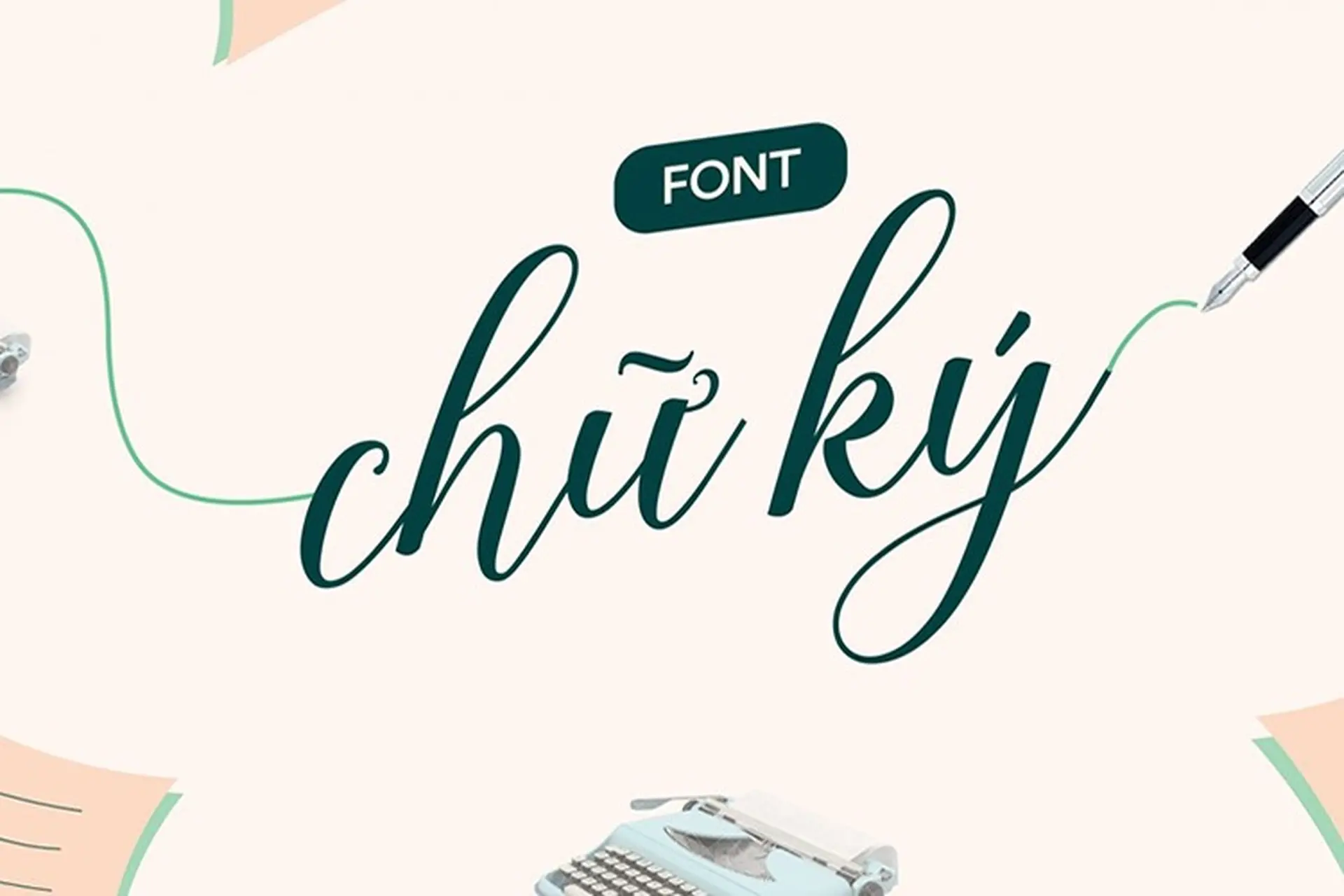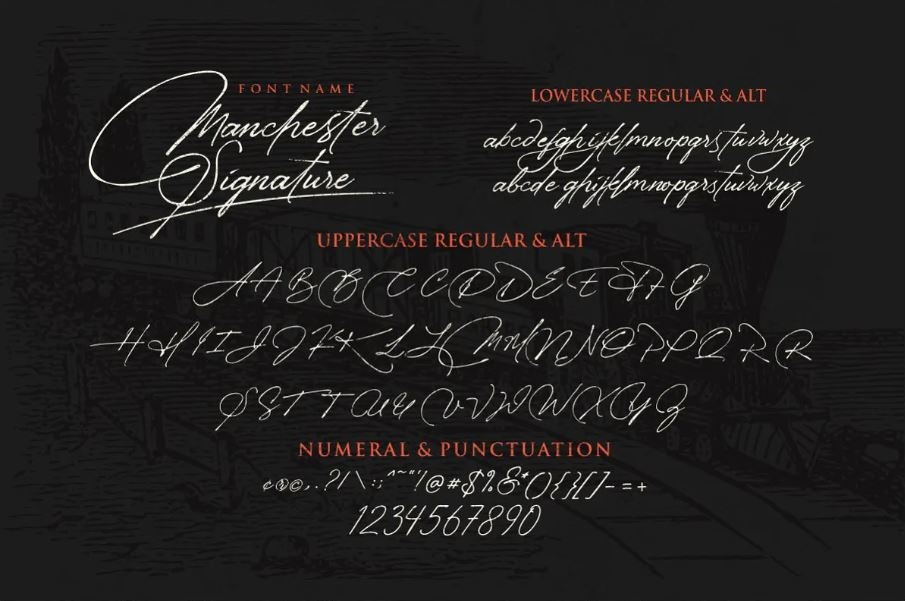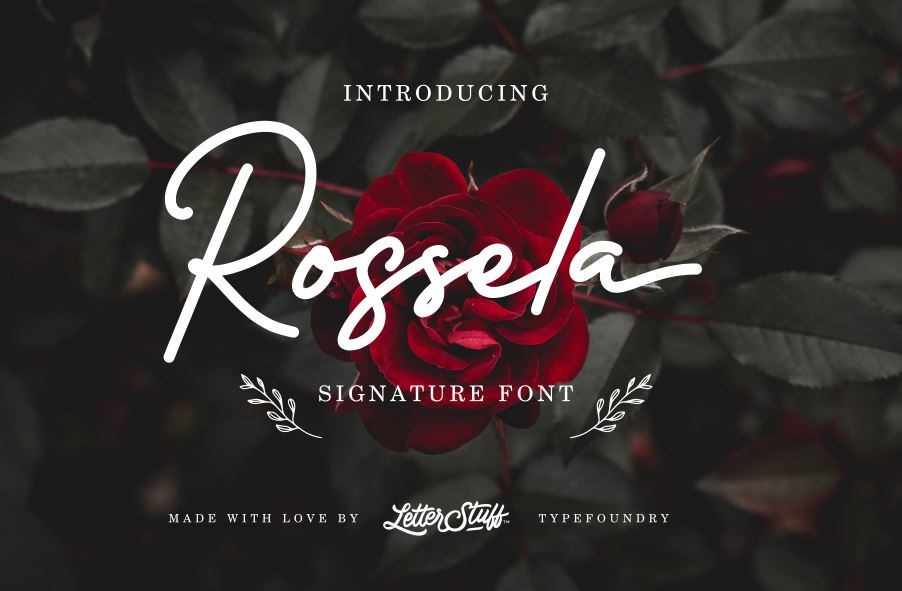
Tổng hợp 10 font chữ ký đẹp, độc đáo được sử dụng phổ biến hiện nay mà bạn nên biết
Sử dụng font chữ ký đẹp là cách để tạo nên những chữ ký ấn tượng và độc đáo. Font chữ được thiết kế với phong cách đa dạng đáp ứng nhu cầu của nhiều người. Trong thiết kế đồ họa, font được sử dụng rộng rãi mang đến những ấn phẩm bắt mắt. Hãy cùng FPT Shop tìm hiểu font chữ ký đẹp phổ biến nhé.
Font chữ ký là một loại font được thiết kế dựa trên các nét chữ ký viết tay của con người. Font chữ sẽ mô phỏng lại các chữ ký thực tế và thể hiện gu thẩm mỹ của chủ sở hữu. Trong bài viết này, FPT Shop sẽ giới thiệu 10 thiết kế font chữ ký ấn tượng nhất hiện nay.
Tại sao bạn nên chọn font chữ ký ấn tượng?
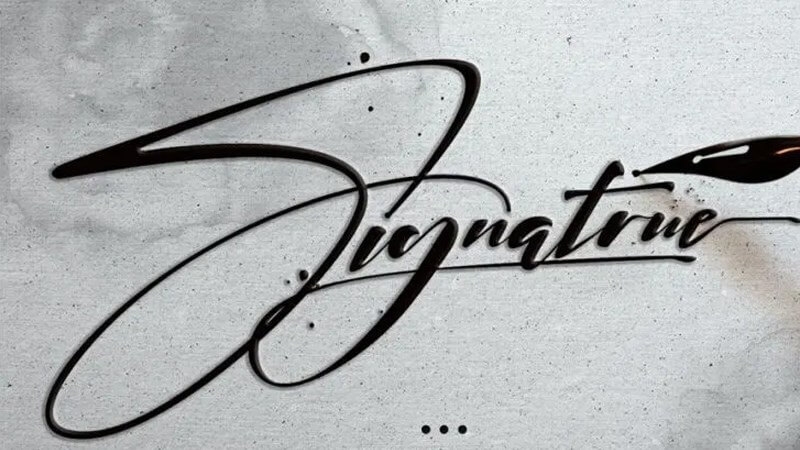
Chữ ký đã quá quen thuộc trong cuộc sống hàng ngày của chúng ta. Mỗi người đều có chữ ký riêng phục vụ cho nhiều mục đích cá nhân khác nhau. Trong thiết kế đồ họa, nét đặc trưng của chữ ký sẽ thể hiện qua font chữ ký mà bạn sử dụng. Font chữ ký ấn tượng không chỉ mô phỏng chân thực mà còn thể hiện tính độc đáo riêng của chữ ký thực tế. Sử dụng font chữ ký đẹp giúp bạn tạo dấu ấn trên nhiều loại ấn phẩm khác nhau như tranh ảnh, bài báo, thiết kế logo, banner quảng cáo,…
Top 10 font chữ ký ấn tượng nhất hiện nay
Dưới đây là top 10 font chữ ký giúp bạn tạo nên những mẫu chữ ký ấn tượng trong các tác phẩm của mình.
1. Font chữ ký Manchester
Font chữ ký Manchester là một font chữ mang đậm chất hoài cổ, tinh tế trong từng đường nét. Font chữ là tổ hợp của chữ cái in hoa và in thường, kết hợp với góc bo tròn mềm mại, dễ nhìn. Vì vậy, font Manchester thường được ứng dụng trong thiết kế logo mang thương hiệu cá nhân.
2. Font chữ ký Quick Signature
Font chữ ký Quick Signature có tính thẩm mỹ cao, thể hiện sự chuyên nghiệp cho người dùng. Đặc biệt, font đã được Việt hoá với 3 bộ dấu lớn nhỏ giúp bạn dễ dàng tạo hình chữ ký trong nhiều trường hợp khác nhau, từ email đến các văn bản chuyên nghiệp. Font cung cấp các thiết kế sẵn theo nhiều phong cách. Tuy nhiên, bạn có thể tuỳ chỉnh nếu muốn thay đổi màu sắc, kích thước hay nét chữ theo sở thích riêng của mình.
3. Font chữ ký Mrattoos Signature
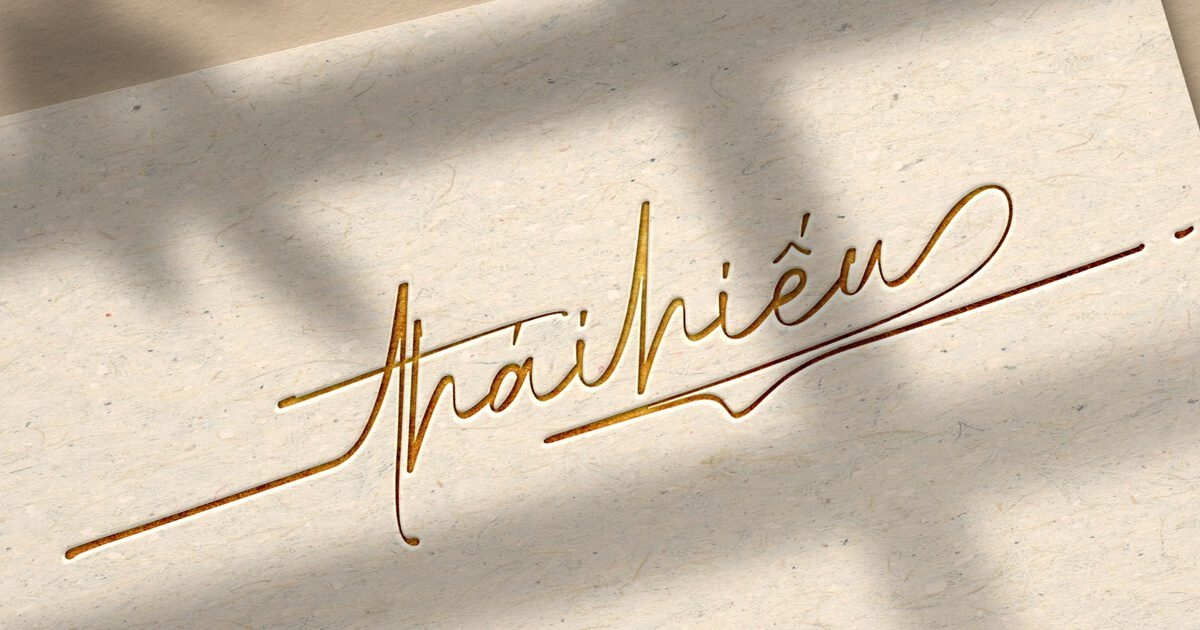
Độc đáo và cá nhân hoá là đặc điểm nổi bật đến từ font chữ ký Mrattoos Signature. Hầu hết người dùng font chữ này là người yêu thích sự khác biệt, chuyên nghiệp và tinh tế trên mỗi tác phẩm. Mrattoons Signature cho phép bạn tùy chỉnh kích cỡ mà không ảnh hưởng tới chất lượng hiển thị của font. Do đó, font chữ ký này được ứng dụng đa dạng với nhiều ngành nghề.
4. Font chữ ký đẹp My Everything
Font chữ ký My Everything có đường nét đơn giản, dễ đọc nhưng vẫn toát lên cá tính, dứt khoát cho người dùng. Font chữ phù hợp với đối tượng như doanh nhân, giáo viên. Nếu yêu thích phông chữ này, bạn có thể dễ dàng cài đặt và sử dụng miễn phí trên nhiều thiết bị.
5. Font chữ ký đẹp The Billion
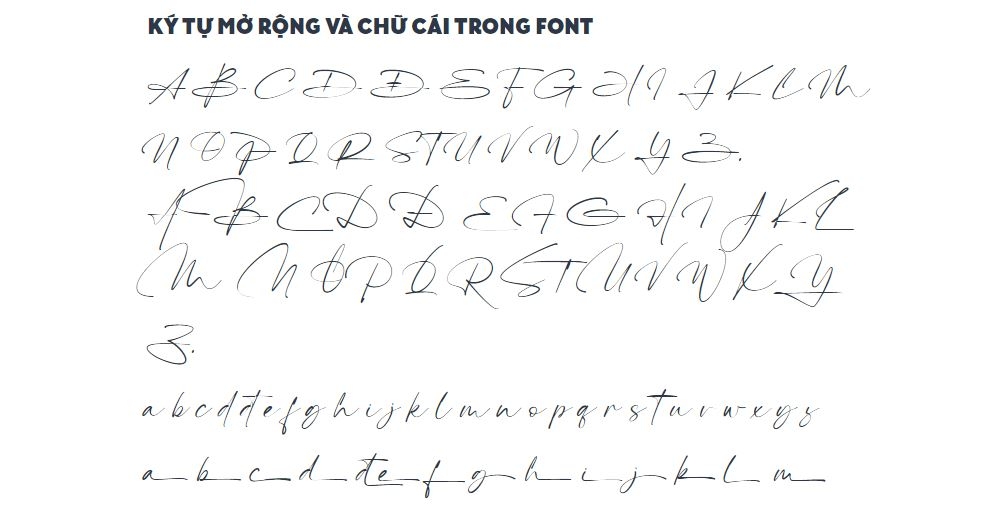
Font chữ ký The Billion được thiết kế đúng với tên “The Billion”, mang đến cho bạn sự sang trọng và tỉ mỉ ngay từ cái nhìn đầu tiên. Font chữ cung cấp đa dạng các định dạng giúp bạn lựa chọn từ chữ in thường đến chữ in đậm. Bạn có thể linh hoạt kết hợp các kiểu dáng với nhau để tạo nên mẫu chữ ký phù hợp với phong cách của mình.
6. Font chữ ký đẹp Sign Rathi
Điểm mạnh của font chữ ký Sign Rathi là phong cách thiết kế tự nhiên, đường nét thanh mảnh. Font chữ ký này rất được ưa chuộng bởi những nhà thiết kế ấn phẩm truyền thông hay bao bì sản phẩm. Ngoài ra, Sign Rathi còn sở hữu 5 bộ ký tự thay thế mô phỏng theo dạng tốc ký cá nhân như gạch chân, nét móc, nét nối,... nên bạn có thể tự do sáng tạo các ý tưởng độc đáo cho chữ ký của mình.
7. Font chữ ký Rossela
Đường nét uốn cong, mượt mà là nét đặc trưng của font chữ ký Rossela. Font chữ ký sử dụng nét cong đơn giản mang lại cảm giác tự nhiên phù hợp với mọi ấn phẩm, đặc biệt là các thiết kế trên bao bì sản phẩm có tính cá nhân hóa. Đây chắc chắn sẽ là gợi ý hoàn hảo nếu bạn muốn ghi lại dấu ấn cá nhân trên mỗi tác phẩm của mình.
8. Font chữ ký Like Father Like Son
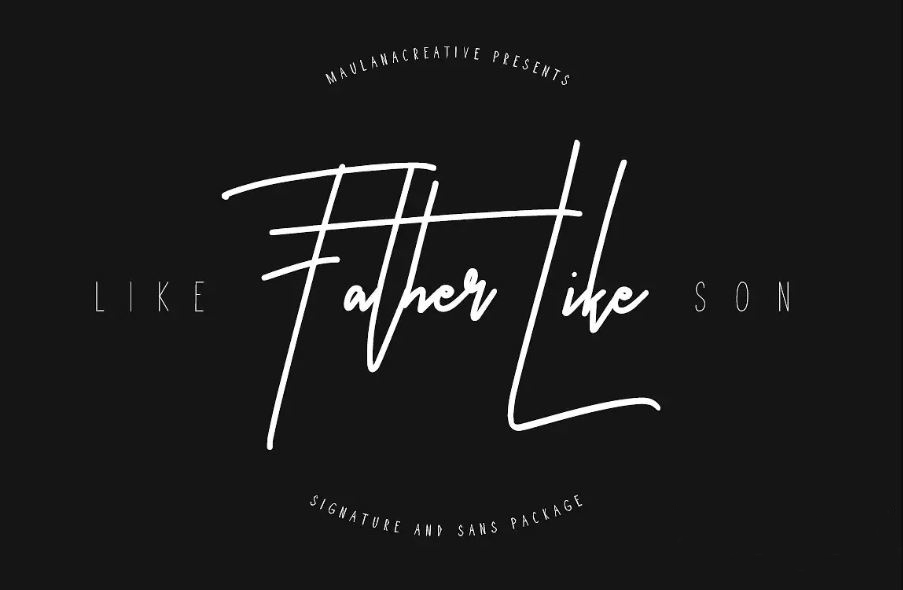
Font chữ ký Like Father Like Son được đánh giá là một trong những font chữ ấn tượng bởi độ phóng khoáng của các chữ cái. Đây có thể coi như một phiên bản chữ ký tay hoàn hảo trong thiết kế đồ họa. Nó không chỉ mang lại cảm giác gần gũi mà còn thể hiện sự tinh tế của người sử dụng.
9. Font chữ ký Just Awesome
Nếu bạn tạo dựng một tác phẩm dễ thương như thiệp mời, hình ảnh trên áo thun thì font chữ ký Just Awesome sẽ đem đến một làn gió tươi mới. Những đường nét bay bổng kết hợp sự cách điệu mềm mại của chữ cái thường sẽ mang lại cảm giác gần gũi với người nhìn.
10. Font chữ ký Scripture
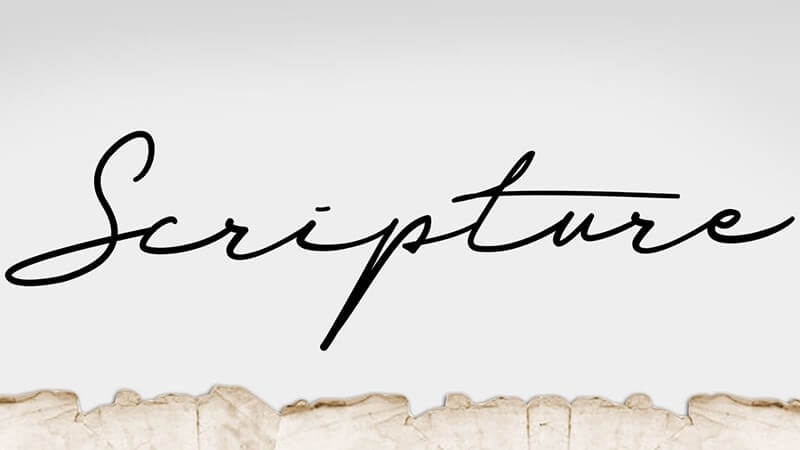
Một trong 10 font chữ ký được tìm kiếm nhiều nhất hiện nay là Scripture. Scripture chỉ đơn thuần là sự kết hợp của Script và Signature nhưng font chữ vẫn có sự thanh thoát nhất định. Vì vậy, font chữ này sẽ giúp chữ ký của bạn toát lên vẻ thanh lịch vốn có, đồng thời tạo nên vẻ tinh tế, khác biệt so với các mẫu font chữ ký khác.